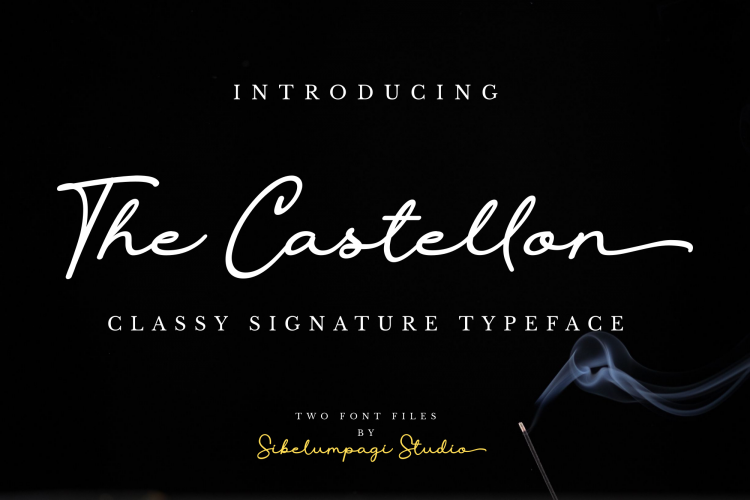
Esta página de download apresenta a The Castellon Script Font, uma elegante tipografia que traz o charme autêntico das escritas manuscritas. Muito cuidadosamente projetada para capturar cada detalhe, incluindo até os mais sutis rasgos e traços, essa fonte foi criada para reproduzir com perfeição a simpatia e delicadeza que encontramos nos textos escritos à mão. Introduzida pelo Sibelumpagi Studio, The Castellon Script é uma seleção perfeita de estilos – regular e inclinado -, oferecendo um toque natural em suas letras. Suas linhas leves e suaves têm um estilo elegante que pode ser incorporado facilmente em sua paleta de design. Ideal para aplicação em projetos variados, como água-marinha nas fotografias, assinaturas, logotipos, citações, marcação e cartões de visita, entre outros. Não se esqueça de experimentar a The Castellon Script Font na sua próxima criação – você certamente notará o brilho adicional que ela adiciona.